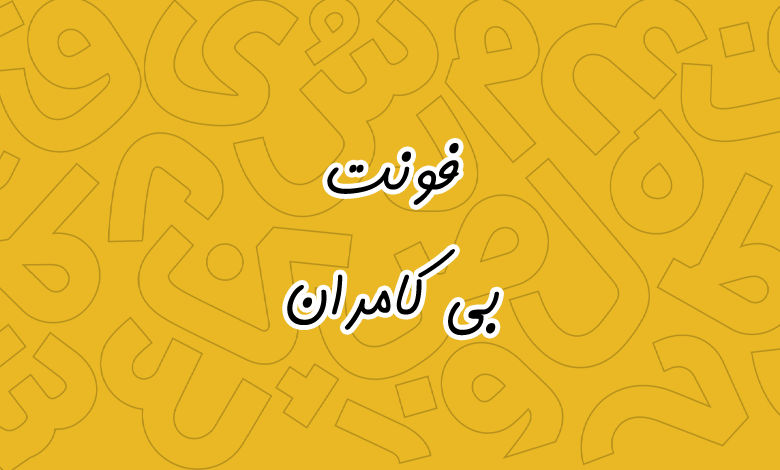
فونت بی کامران (B Kamran)
فونت بی کامران یا کامران (به انگلیسی: B Kamran) قلمی متفاوت از سری فونتهای بی است که علاوه بر پشتیبانی از دو وزن، دارای یک سبک دورخط (outline) نیز میباشد. این فونت فارسی رایگان دارای سبک دستنویس است که میتوانید برای کارهای فانتزی و نمایشی از آن استفاده کنید. در ادامه با دانلود رایگان فونت بی کامران با شما همراه هستیم.
فونت b kamran دارای ظاهری دست نویس است که حروف در آن دارای ظاهری ایتالیک هستند. همچنین در این فونت از سبک نقطهگذاری گرد استفاده شده که ظاهر فونت را صمیمیتر کرده است. در تصویر زیر پیشنمایش این فونت از هر سه سبک را مشاهده میکنید.
فونت فارسی بی کامران به لطف یکسان بودن با رسمخط عربی از این زبان نیز پشتیبانی میکند. بهطوری که بر اساس تنظیمات زبان در برنامههای گرافیکی مانند فتوشاپ یا برنامههای آفیس، اعداد به صورت فارسی یا عربی تایپ خواهند شد. علاوه بر این اعراب و حروف عربی که ظاهری متفاوت با زبان فارسی دارند در این قلم گلیف اختصاصی خود را دارند.
در مقابل برای زبان انگلیسی دارای سبک طراحی خاص و دستنویس نیست و اگر بهصورت ترکیبی از زبان فارسی و لاتین استفاده میکنید، لازم است که از فونت دیگری برای حروف لاتین استفاده کنید. در این فونت حروف انگلیسی با فونت پیشفرض تایپ میشوند.
ظاهر تمامی حروف در فونت بی کامران تا حدی ایتالیک است که آن را نمایشی کرده است. نقاط از یک سبک گرد بهره میبرند و زوایا و دایرهها طوری هستند که کمی از شدت آنها کاسته شده است. در بسته دانلود رایگان فونت کامران ۳ سبک زیر قرار داده شده است:
از فونت بی کامران میتوانید برای تبلیغات بهویژه در مجلات، بیلبوردها و روزنامهها که بیشتر با حوزه کودک و نوجوان سر و کار داشته باشد استفاده کنید. از دیگر کاربردهای این قلم، فونت مناسب نام و جلد کتاب است. اگر به دنبال دانلود فونت رایگان برای کپکات هستید، وزن دورخط این قلم میتواند برای استفاده در تامنیل ویدئوها یا زیرنویس فیلم و سریال مورد استفاده قرار گیرد.